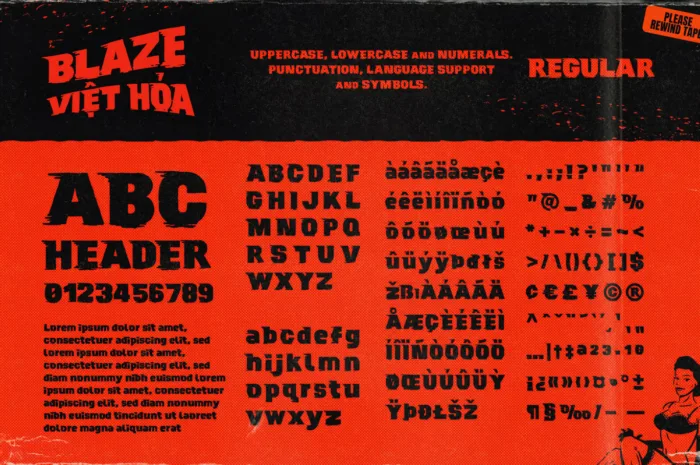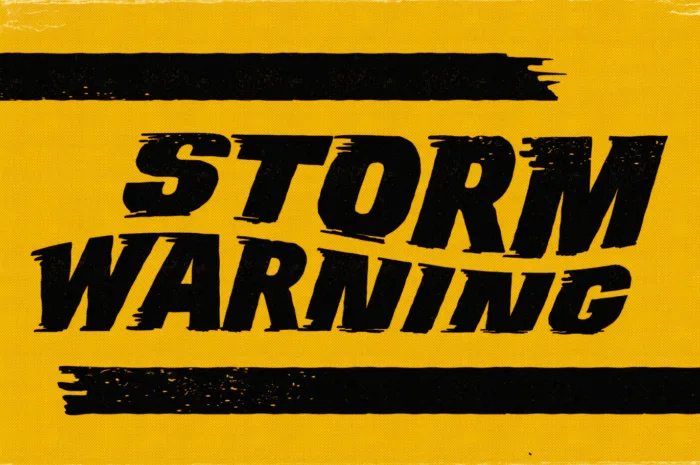
DVN Blaze Việt hóa – Font chữ mạnh mẽ, bùng nổ năng lượng và tốc độ
DVN Blaze là một font chữ đậm chất hành động với phong cách mạnh mẽ, góc cạnh và đầy tốc độ. Lấy cảm hứng từ những cuộc rượt đuổi gay cấn, những pha bứt tốc cháy đường, DVN Blaze mang đến sự dứt khoát, quyết liệt trong từng nét chữ. Font đặc biệt phù hợp với các thiết kế về thể thao, xe cộ, game, poster hành động hoặc branding mang hơi hướng năng động.
Phiên bản Việt hóa của DVN Blaze giữ nguyên tinh thần mạnh mẽ vốn có, đồng thời tối ưu hóa dấu tiếng Việt để đảm bảo hiển thị sắc nét, hài hòa. Nếu bạn đang tìm kiếm một font chữ ấn tượng để tạo điểm nhấn cho thiết kế của mình, DVN Blaze chắc chắn là một lựa chọn không thể bỏ qua. Hãy tải ngay và trải nghiệm sự bùng nổ của tốc độ trong từng con chữ!